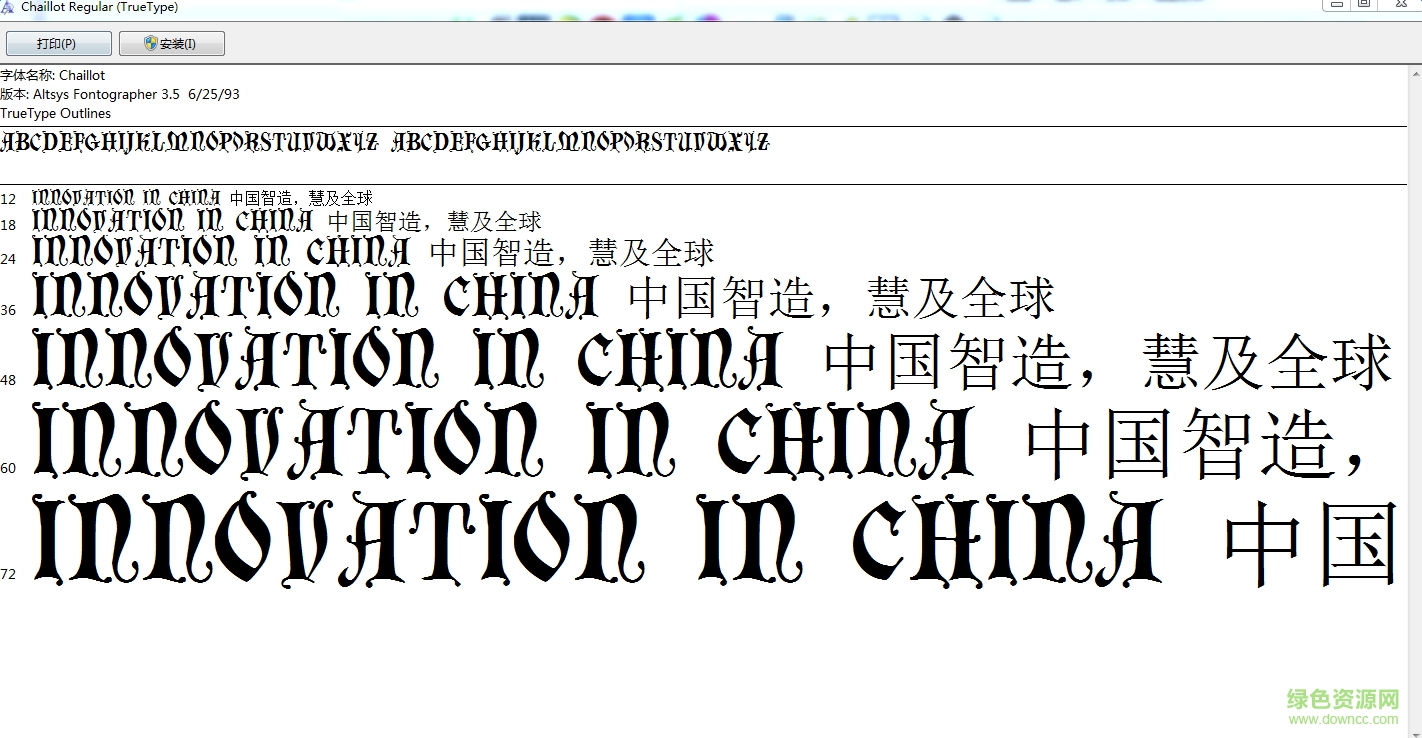
Chaillot字體是一款英文字體軟件,字體工整,獨(dú)特的英文風(fēng)格給人非常舒服的感覺,深受廣大年輕人以及書法家的喜愛,還有更多好看字體盡情期待,歡迎到綠色資源網(wǎng)下載體驗(yàn)!
Chaillot字體是一款的英文字,字體效果比較西方化,喜歡英文字體的朋友可以下載使用看看效果如何。